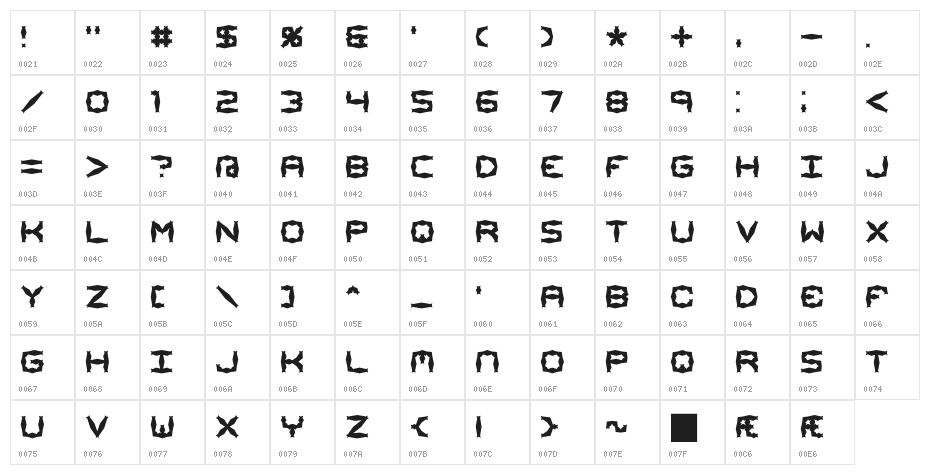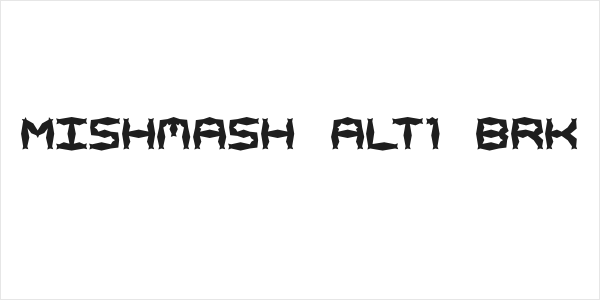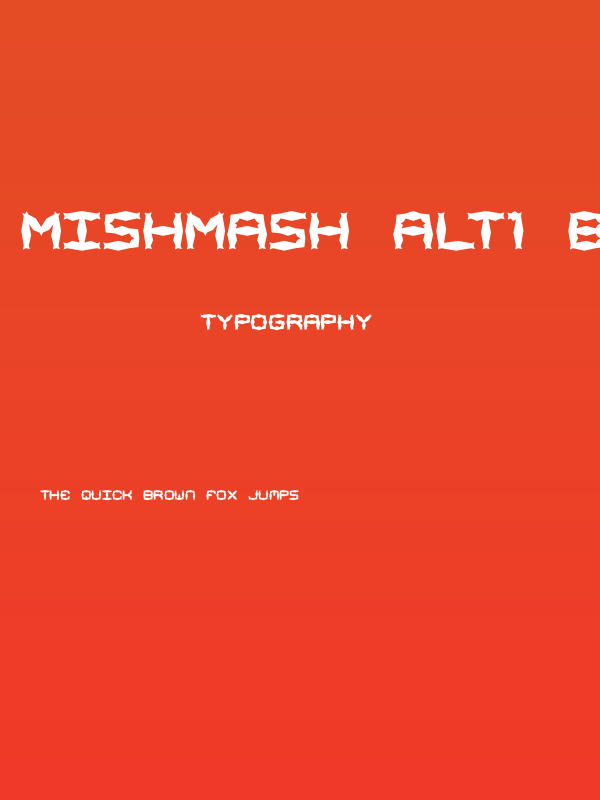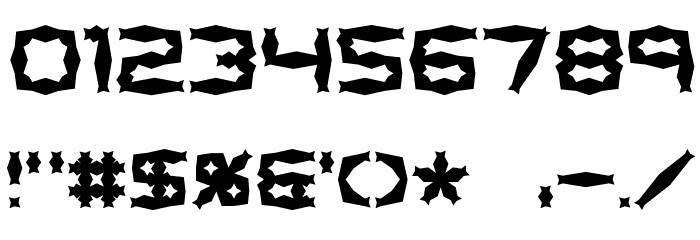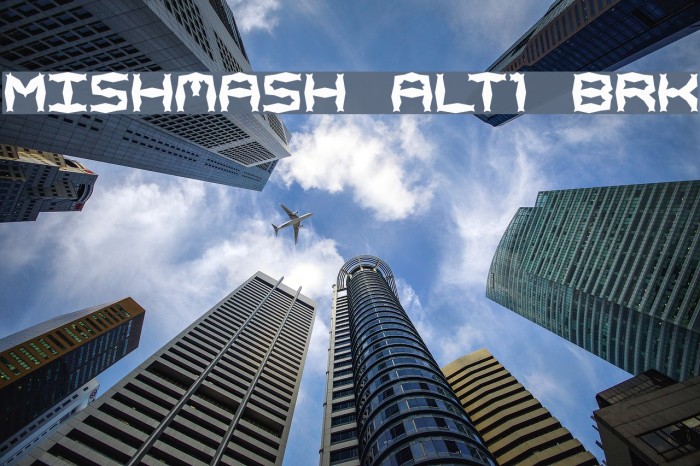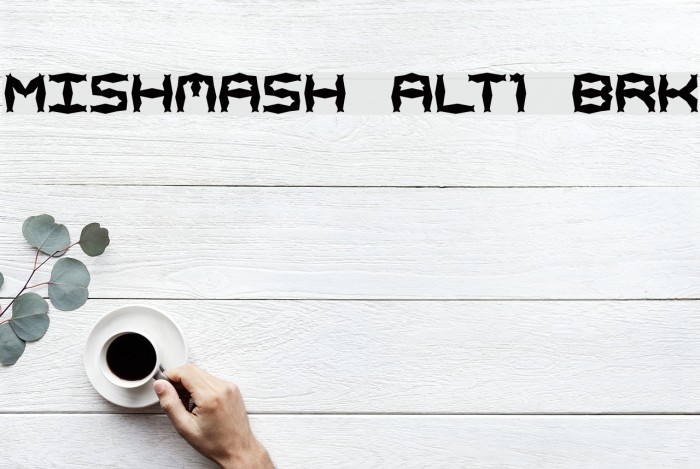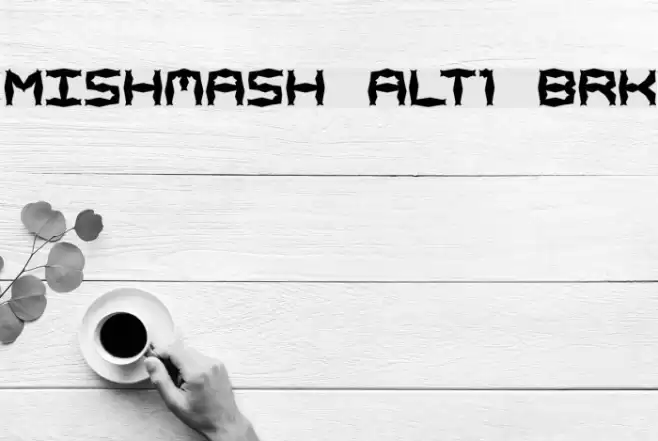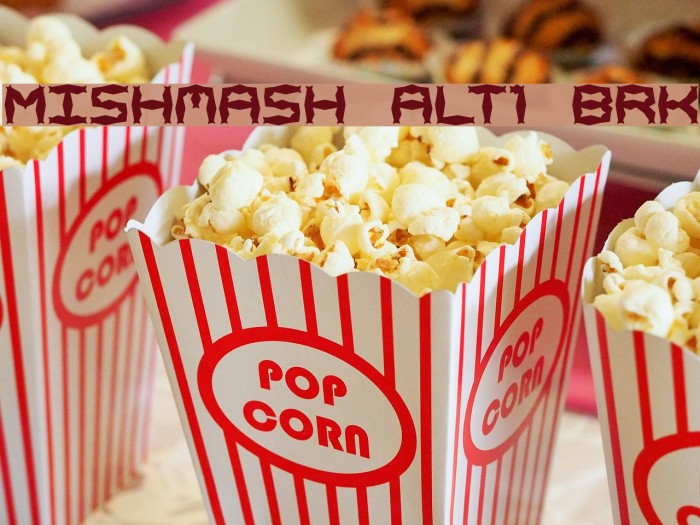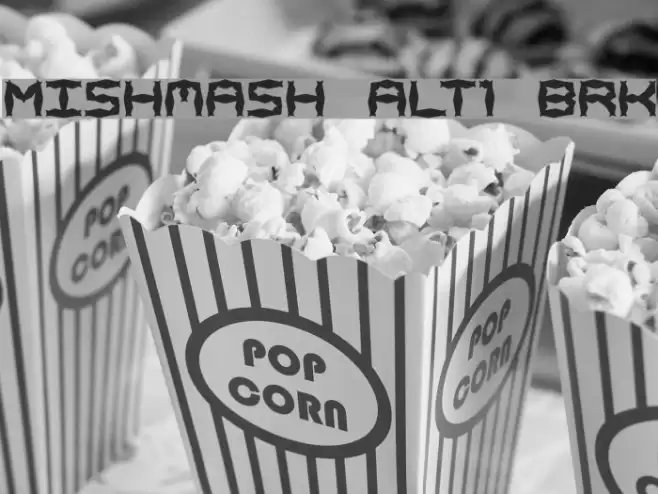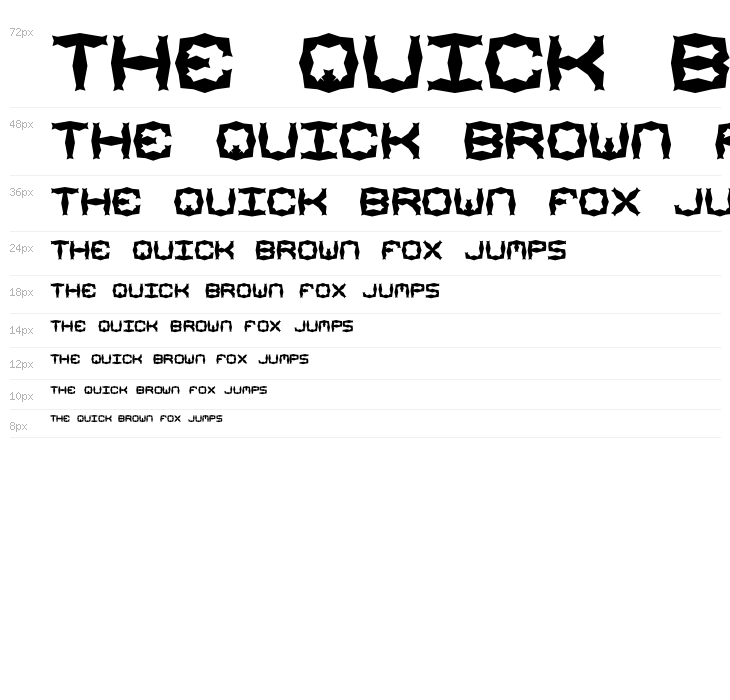
Mishmash ALT1 BRK Font
| Proyectos propuestos | Ideal for album covers, posters, video game titles, and any project requiring a bold, edgy aesthetic. |